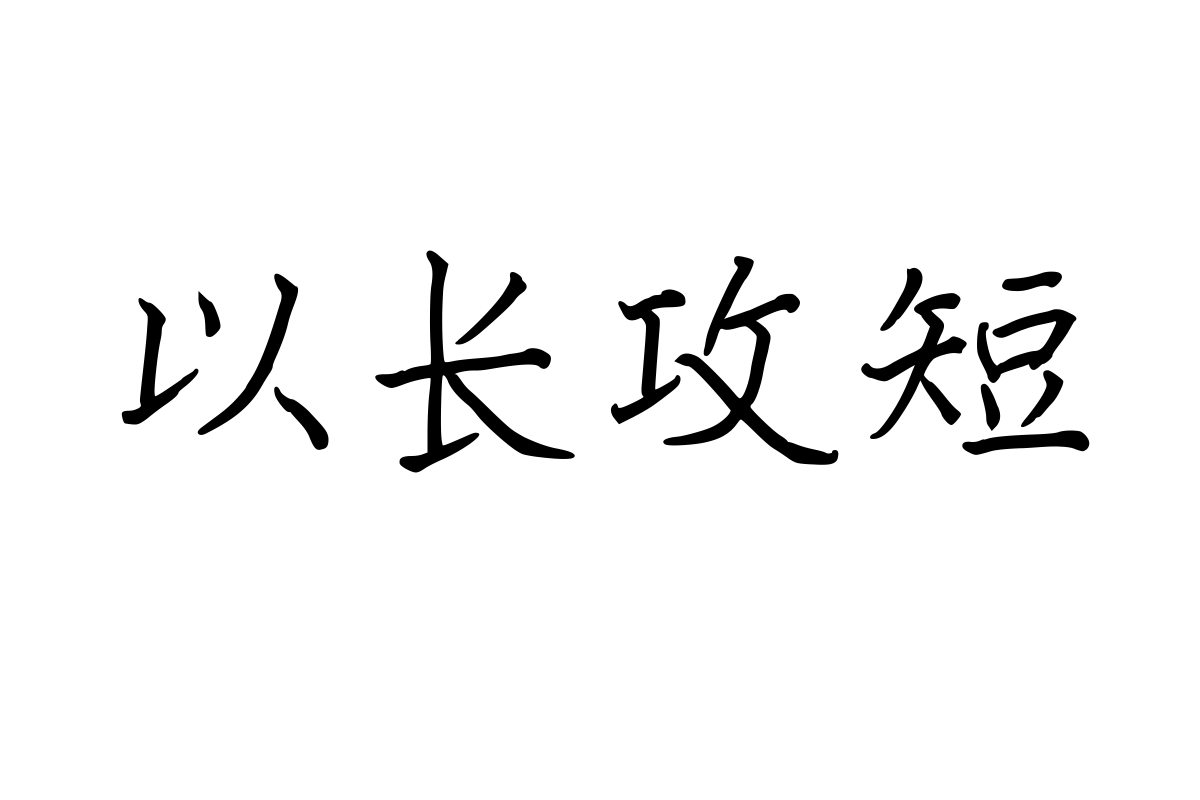
蝉羽卿颜若水是一款具有独特艺术风格的字体,其特点如下:
1. 字形优美:蝉羽卿颜若水字体的字形流畅自然,线条柔和,给人以优雅、清新的感觉。
2. 结构紧凑:该字体的结构紧凑,笔画之间相互呼应,整体呈现出一种和谐统一的效果。
3. 风格独特:蝉羽卿颜若水的字体风格独特,既有传统书法的韵味,又不失现代感,给人一种新颖、独特的视觉体验。
4. 适用范围广泛:蝉羽卿颜若水字体适用于各种设计领域,如书籍封面、广告宣传、网页设计等,具有较高的实用价值。
总之,蝉羽卿颜若水是一款独具特色的字体,其优美的字形、紧凑的结构、独特的风格和广泛的应用范围使其成为设计师们的首选字体之一。